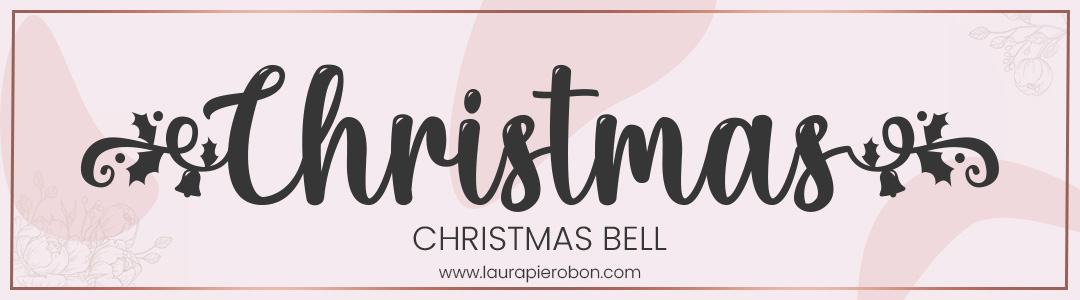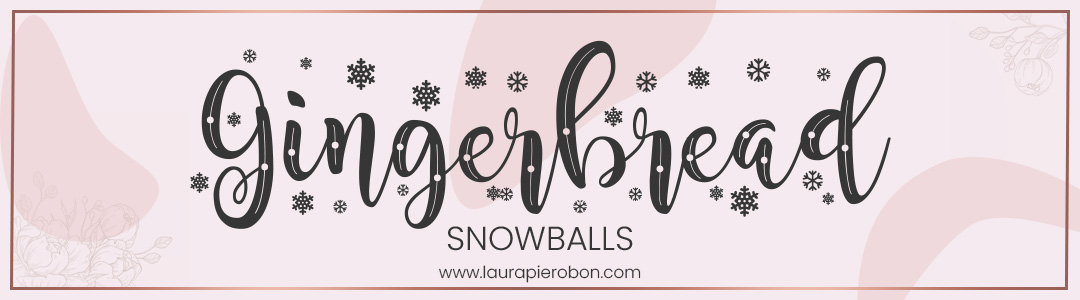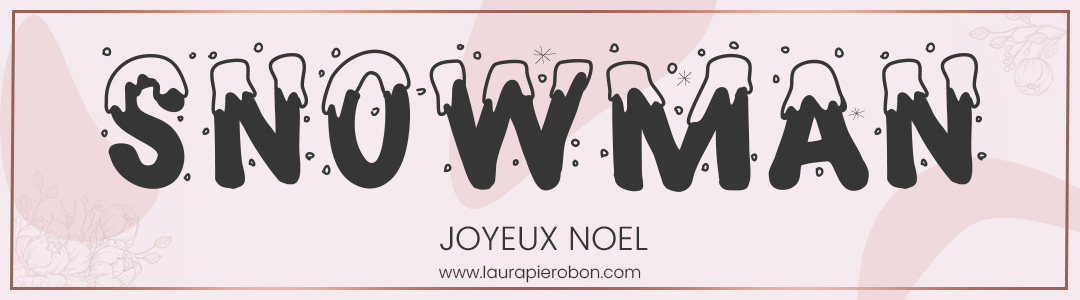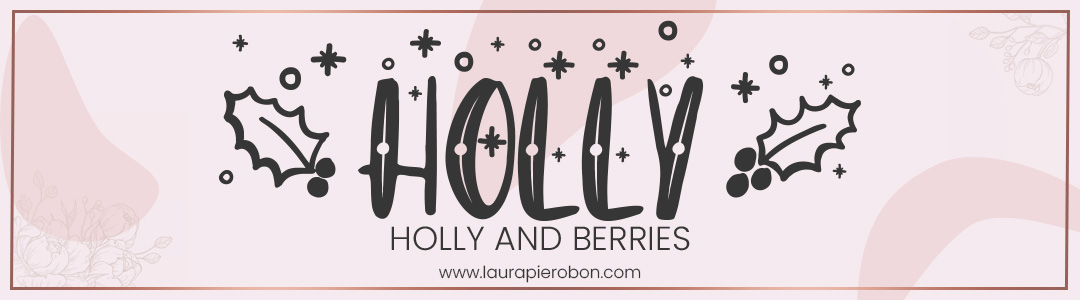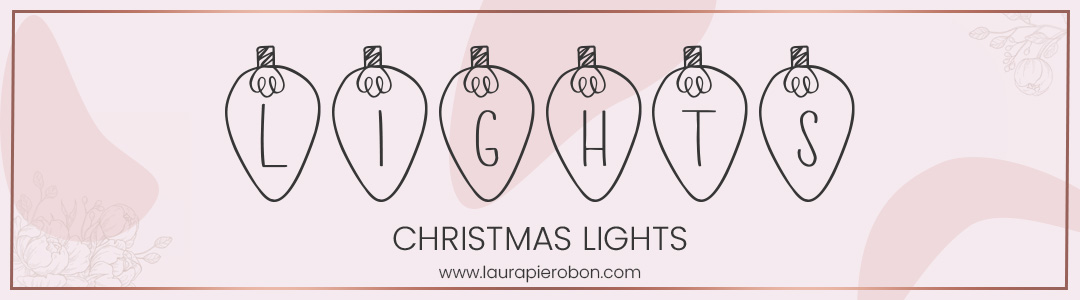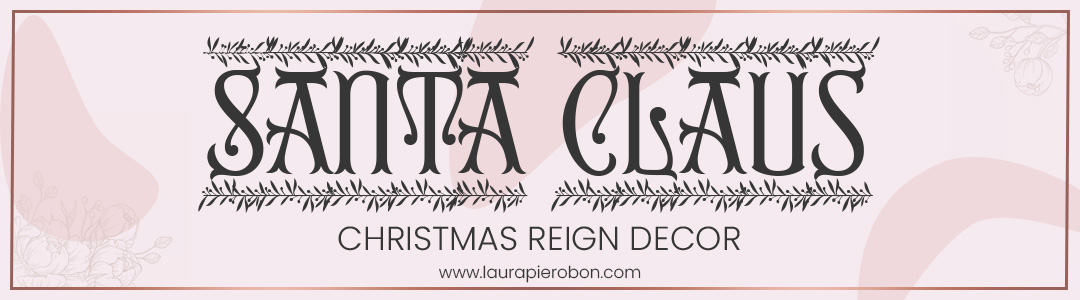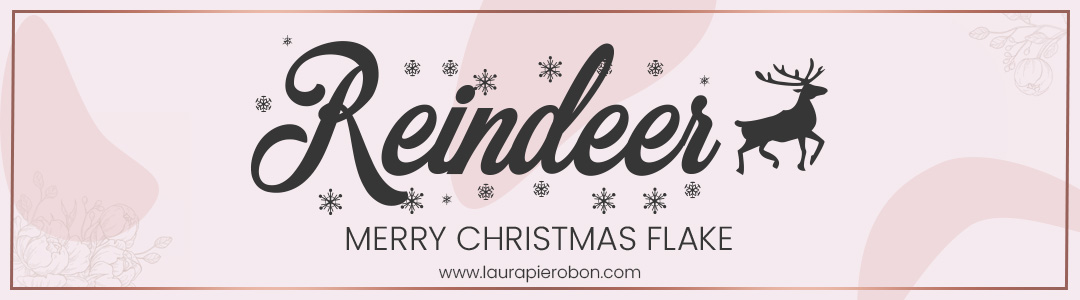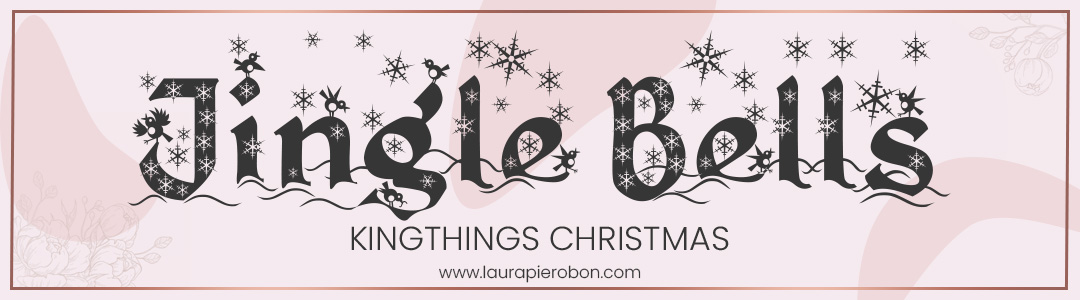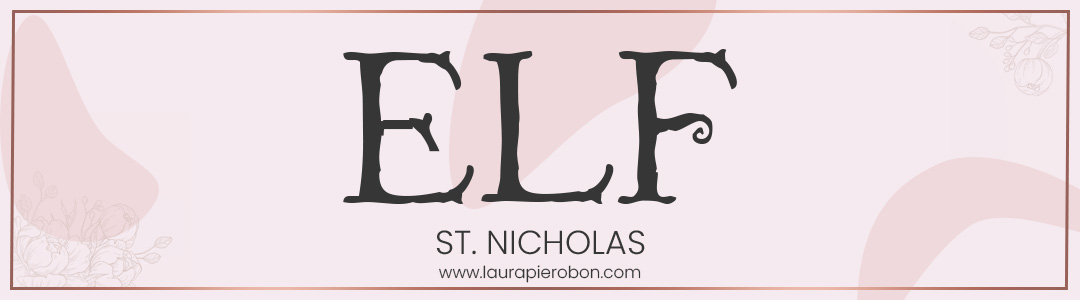
Anche tu, come me, adori il Natale? 🎄
Le lucine, le musiche, i biscotti appena sfornati e quell’atmosfera magica che scalda il cuore… non c’è periodo dell’anno più luminoso e pieno di gioia!
E allora perché non portare un po’ di quello spirito anche nelle tue creazioni grafiche?
Che tu stia realizzando biglietti d’auguri, inviti per feste, etichette regalo, grafiche per i social o banner per il tuo shop, il font giusto può trasformare un semplice progetto in qualcosa di davvero speciale.
Per aiutarti, ho preparato una raccolta di 10 font festivi e gratuiti, tutti scaricabili da Dafont.com, perfetti per trasmettere calore, allegria e un pizzico di magia natalizia! ✨
🎅🏻 10 font natalizi da scaricare subito
Christmas Bells – Classico e raffinato, con decorazioni che ricordano le campanelle di Natale. Perfetto per biglietti o copertine eleganti.
Snowballs – Giocoso e allegro, con piccoli fiocchi di neve che decorano ogni lettera, perfetto per trasmettere tutta la magia delle giornate d’inverno.
Joyeux Noël – Un font decorativo con lettere innevate e un aspetto elegante, perfetto per auguri classici e grafiche natalizie dallo stile tradizionale.
Holly and Berries – Ricco di dettagli natalizi, con agrifoglio e bacche che decorano le lettere. Perfetto per grafiche e card artigianali.
Christmas Lights – Vivace e luminoso: un font che sembra illuminarsi come una fila di lucine colorate.
Christmas Reign Decor – Elegante e scenografico, con linee calligrafiche e ornamenti che lo rendono perfetto per titoli o inviti raffinati.
Merry Christmas Flake – Allegro e decorativo, con fiocchi di neve che impreziosiscono le lettere. Perfetto per grafiche gioiose e divertenti.
Kingthings Christmas – Originale e giocoso, ricorda le scritte dei biglietti vintage. Ottimo per materiali dal gusto retrò.
St. Nicholas – Dal nome del “vero” Babbo Natale, questo font ha un fascino classico e caldo, perfetto per testi e loghi.
Candy Cane – Ispirato alle caramelle a righe bianche e rosse: dolce, simpatico e perfetto per i progetti più allegri e informali.